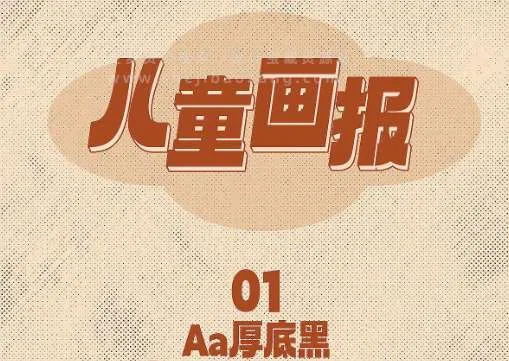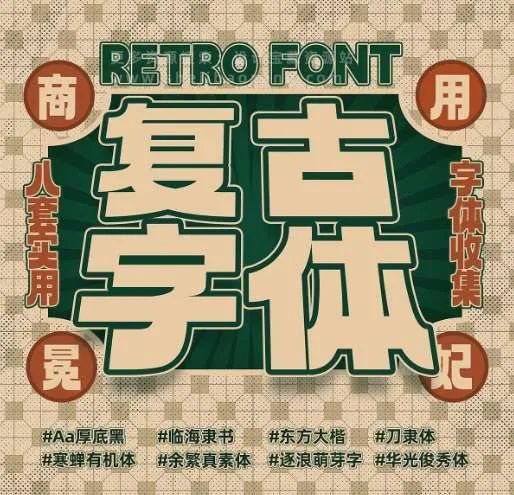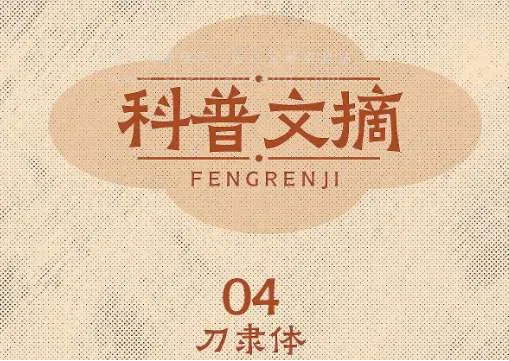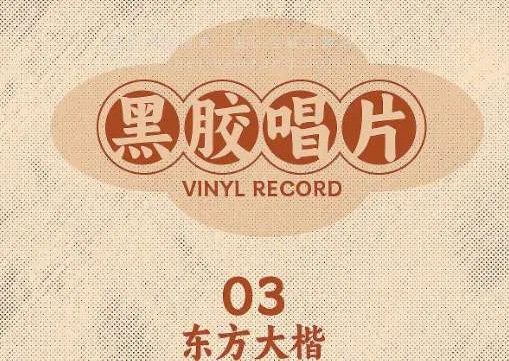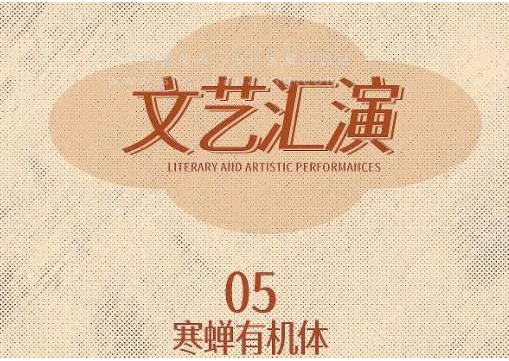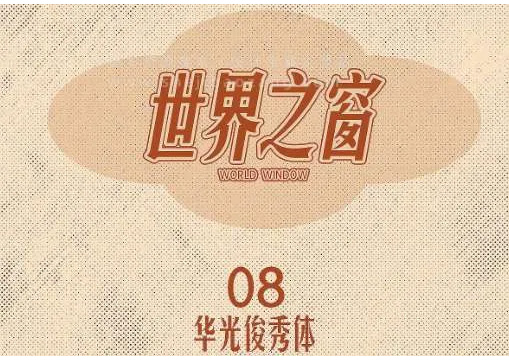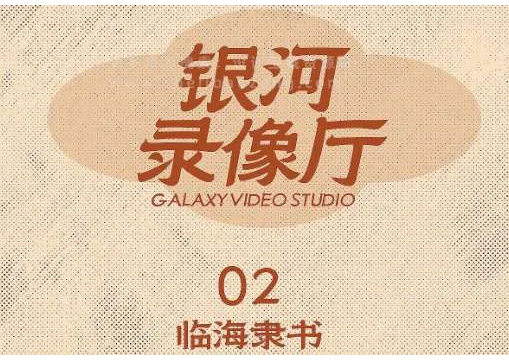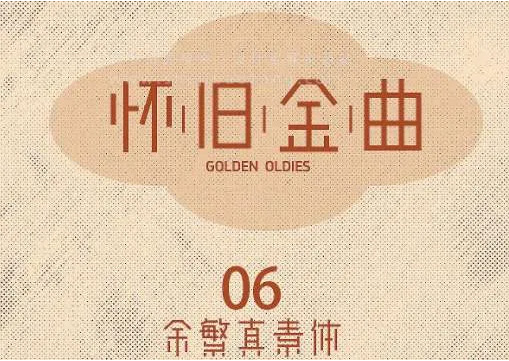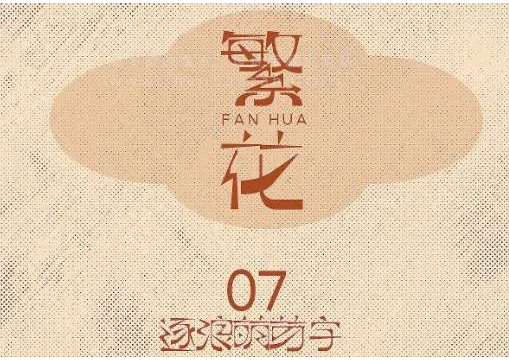
8款免费可商用怀旧复古字体下载
复古风格字体凭借其独特的历史韵味与艺术表现力,能为设计作品注入经典质感。以下推荐8款可免费商用的复古字体方案,助力设计师打造兼具传统与个性的视觉呈现:
1;Aa厚底黑
以粗犷笔画构建强烈视觉层次,特别适合海报主标题及需要突出视觉焦点的设计场景。
2;阿里刀隶体
取法传统隶书笔意,线条遒劲流畅,是文化类主题设计(如博物馆导视、国学宣传物料)的优质选择。
3;阿里东方大楷
承袭楷书端方气度,字形结构严谨稳重,适用于政府公文、企业年报等正式场合的版式设计。
4;寒蝉有机体
从自然形态中萃取设计灵感,笔画间蕴含生长韵律,适合生态环保类主题的创意表达。
5;华光俊秀体
以纤细俊朗的线条塑造现代优雅感,在时尚杂志排版及艺术展览海报中能展现独特气质。
6;临海隶书
复刻古碑帖神韵,兼具古拙与雅致,特别适配古籍封面、文化期刊等传统出版物的标题设计。
7;余繁真素体
在极简造型中暗藏细节巧思,实现现代极简主义与传统书写的有机融合,适合文创产品包装设计。
8;逐浪萌芽字
创新笔触模拟新芽破土之势,充满青春张力,尤其契合潮牌LOGO、青少年品牌等年轻化视觉系统。
这组字体库既保留传统书法精髓,又经过数字化适配优化,全部支持免费商用授权。设计师可根据项目调性自由组合,在历史感与现代性之间构建独特的视觉叙事语言,有效降低设计成本的同时提升作品文化内涵。